Systemschriften
»Systemschriften« ist in der IT und Typografie eine Bezeichnung für Screen Fonts (Bildschirmschriften), die ein Betriebssystem (OS Operating Systems, z.B. Microsoft Windows ® oder Apple macOS ®) eines Mikrocomputers (PC, Smartphone, Tablet, Watch etc.) sowie dessen Anwendersoftware (z.B. Textverarbeitungsprogramme, Web Browser oder E-Mail Clients) im Rahmen der visuell basierenden Benutzerkommunikation (z.B. über LCD-Monitore, Multi-Touch Displays oder sonstige optische Interfaces) benötigt. Auch als Systemschriftarten, System Fonts oder Interface Fonts bezeichnet.
Systemschriften werden in der Regel bei der Erstinstallation und bei Updates (Softwareaktualisierungen) des Betriebssystems durch den jeweiligen Hersteller (z.B. Apple ®, Microsoft ® oder Google ®) auf dem Startvolumen oder einem Primärspeichermedium (z.B. eine Festplatte) installiert.
Primäre Systemschriften
Systemschriften lassen sich in Primär- und Sekundärsystemschriften abgrenzen, wobei die Primärsystemschriften als Mindestanforderung für ein Betriebssystem bzw. die bereitgestellte Software benötigt werden. Im Zuge der globalen Kommunikation zählen auch Nichtrömische Schriften und Zeichen zu den Systemschriften. Welche Screen Fonts zu den primären und sekundären Systemschriften zählen, hängt vom jeweiligen Betriebssystem und der jeweiligen OS-Version ab.
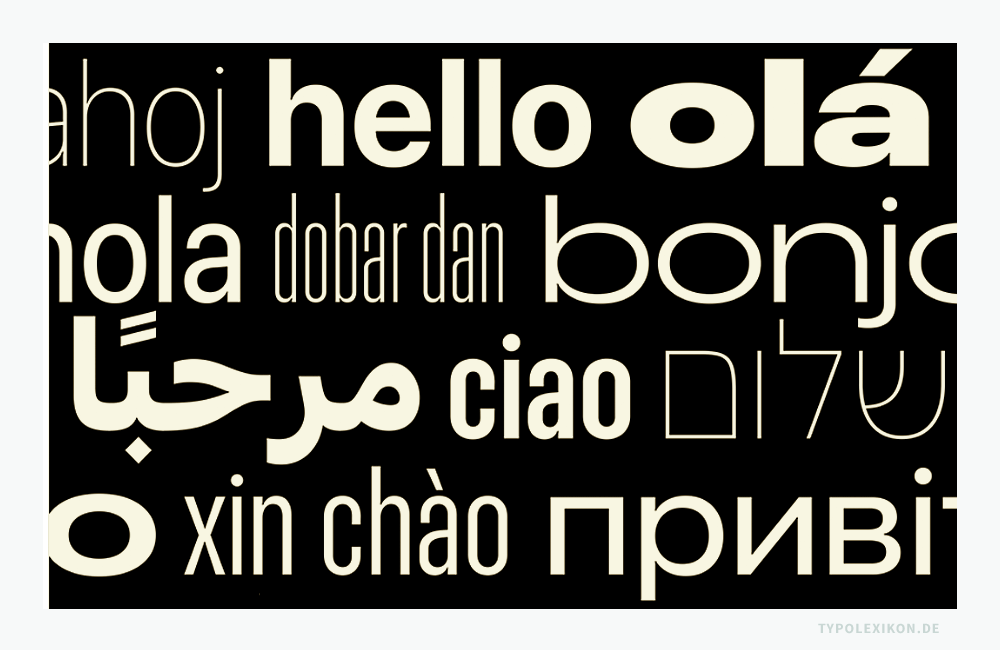
Beispielsweise änderte Apple ® seinen primären System Font »Lucida Grande« von Charles Bigelow (* 1945) und Kris Holmes (* 1950) über die »Helvetica« von Max Miedinger (1910-1980) hin zur »San Francisco« (SF Pro, SF Compact und SF Mono), 1) einer selbst entwickelten serifenlosen Schriftart für alle Apple-Geräte, die insbesondere für die Lesbarkeit auf kleinen Bildschirmen (z.B. iPhone ® oder Apple Watch ®) bei kleinen Schriftgraden optimiert wurde. Der Font San Francisco ist allerdings ausschließlich für registrierte Entwickler von Drittanbietern für die Entwicklung von Anwendungen der Betriebssysteme iOS, iPadOS, macOS und tvOS lizenziert. 2)
Das Pendant zu Apples »San Francisco« ist die »Segoe UI Variable« von Microsoft ®, 3) ein Variabler Font, der den System Font »Tahoma« von Matthew Carter (*1937) bzw. den Vorgänger, die »Arial« von Robin Nicholas (*1947) und Patricia Saunders (1933–2019), abgelöst hat.
Primäre Systemfonts können oder sollten nicht gelöscht oder geändert werden, da sie von von der gesamten Softwarearchitektur benötigt werden. So ist beispielsweise die San Francisco von Apple ® (SF Pro, SF Compact und SF Mono) nur für Entwickler gedacht, nicht für den User. Deshalb ist dieser Primärsystemfont auch nicht in der Schriftensammlung für den User sichtbar.
Primäre Systemschriften, Apple macOS:
| Schrift | Klassifikation | Schriftschnitte | Dickte | Format |
|---|---|---|---|---|
| San Francisco SF Pro | Sans Serif | Unterschiedliche Strichstärken und variable Optische Größen | Proportional | Variabler Font |
| San Francisco SF Compact | Sans Serif | Systemschrift für watchOS Konsultations- größen | Proportional | Variabler Font |
| San Francisco SF Mono | Sans Serif | Unterschiedliche Strichstärken | Monospaced | Variabler Font |
| New York | Serif | Unterschiedliche Strichstärken und variable Optische Größen | Proportional | Variabler Font |
| San Francisco SF Arabic | Nichtrömische Schrift | Unterschiedliche Strichstärken und variable Optische Größen | Proportional | Variabler Font |
| San Francisco SF Armenian | Nichtrömische Schrift | Unterschiedliche Strichstärken und variable Optische Größen | Proportional | Variabler Font |
| San Francisco SF Georgian | Nichtrömische Schrift | Unterschiedliche Strichstärken und variable Optische Größen | Proportional | Variabler Font |
| San Francisco SF Hebrew | Nichtrömische Schrift | Unterschiedliche Strichstärken und variable Optische Größen | Proportional | Variabler Font |
Primäre Systemschrift, Microsoft Windows ab V. 11:
| Schrift | Klassifikation | Schriftschnitte | Dickte | Format |
|---|---|---|---|---|
| Segoe UI Variable | Sans Serif | Unterschiedliche Strichstärken und variable Optische Größen | Proportional | Variabler Font |
Sekundäre Systemschriften
Sekundäre Systemschriften sind im Wesentlichen eine Art »Dreingabe« des Herstellers, die eine unkomplizierte Textkommunikation mit einem Mikrocomputer ermöglichen soll. Sie dienen primär der visuellen Text- und Bürokommunikation über eine Anwendersoftware, z.B. für das Schreiben eines Briefes in Microsoft Word ® oder Apple Pages ®, dem Betrachten einer Website in einem Internet-Browser (Clients, z.B. Safari ®, Chrome ® oder Firefox ® etc.) oder für Präsentationen mittels Microsoft PowerPoint ® oder Apple Keynote ®.
Sekundäre Systemschriften, Apple macOS, ohne Nichtrömische Schriften:
| Schrift | Klassifikation | Schriftschnitte | Dickte | Format |
|---|---|---|---|---|
| Academy Engraved LET | Zierschrift Serif | Normal | Proportional | TrueType |
| American Typewriter | Slab Serif | Leicht Normal Halbfett Fett Schmalmager Schmal Fett Schmal | Proportional | TrueType |
| Andalé Mono | Sans Serif | Normal | Monospaced | OpenType TrueType |
| Apple Color Emoji | Emojis | normal | Proportional | TrueType |
| ↑4 | Anmerkung: Das Suffix *.otf wird hauptsächlich für OpenType PostScript® flavoured verwendet. Allerdings erlauben die OpenType-Spezifikationen, dass auch OpenType TrueType flavoured Fonts diese Endung verwenden können. Also Vorsicht beim Kauf eines Fonts! |
| ↑6 | Anmerkung: Auf Google Android ® finden sich keine dieser Schriften! |